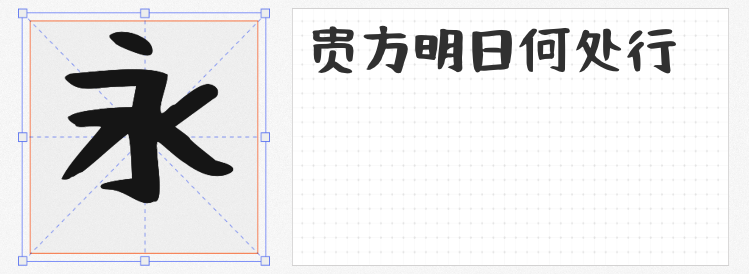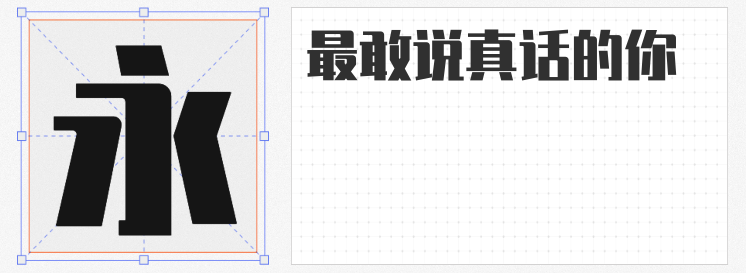
父亲节将至,如何用设计传递父爱的力量与温度?除了画面,字体的选择同样关键。今天推荐四款免费商用字体,兼具力量感与情感表达,助你打造令人印象深刻的父亲节海报。
1. 锐字潮牌真言简2.0免费 超粗
这款字体笔触浑厚有力,笔画转折间刚柔并济,直角与圆角的错落搭配赋予字体独特的节奏感。其端正凝练的气质,既适合表现父亲的沉稳可靠,又能通过细节处的婉转设计传递温情。在父亲节海报中,可用于标题或核心文案,瞬间抓住观众视线。
2. 平方张亚玲黑方体
作为一款融合黑体与卡通特性的艺术字体,它以活泼的笔触和夸张的造型打破传统设计的沉闷感。若想在父亲节海报中展现父子间的亲密互动或幽默场景,这款字体是绝佳选择。其趣味性设计既能传递轻松氛围,又不失黑体的稳重感,适合搭配插画或照片使用。
3. 阿里妈妈刀隶体
这款字体以爨宝子碑为灵感,通过三角点折弯与“雁尾”笔画的夸张处理,展现出隶书与楷书交融的独特韵味。其结构大胆、布白出人意料,既保留了古朴的稚拙感,又暗含动态张力。在父亲节海报中,可用于强调“传承”“岁月”等主题,搭配复古色调或水墨元素,瞬间提升文化底蕴。
4. 可爱手写体
基于毛笔字优化视认性设计,这款字体在保留手写温度的同时,确保了商业场景下的易读性。其收录的9000余个汉字,覆盖日常用字与趣味变体,尤其适合表现“父爱如山”的细腻情感。在海报中,可用于书写父亲寄语或孩子的心声,搭配暖色调与手绘元素,瞬间拉近与观众的距离。
父亲节海报的设计,既要传递力量感,也要表达温情。这四款免费商用字体,从刚劲到柔美,从古朴到现代,满足不同风格的创意需求。无论是突出父爱的深沉,还是展现父子间的欢乐互动,它们都能成为海报的点睛之笔。立即下载使用,让你的父亲节设计更具感染力!